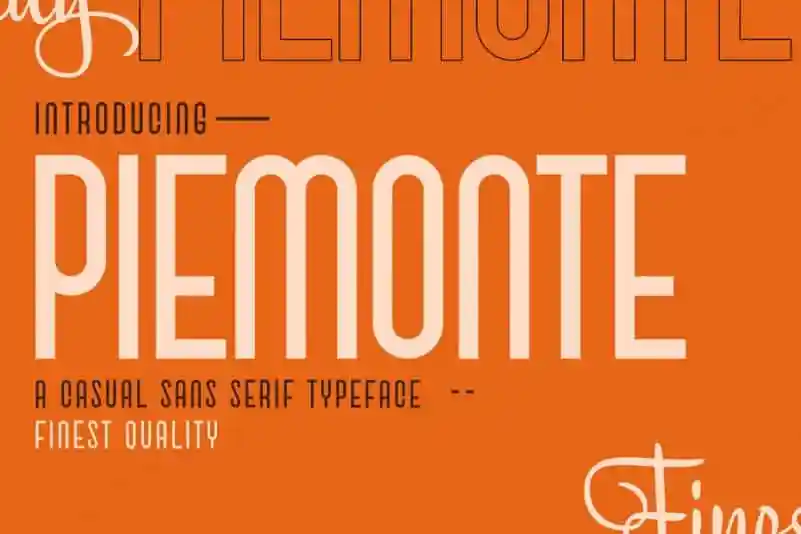
Piemonte Sans Serif Font – Download Grátis
A Pieto Sans Serif Font é uma tipografia séria moderna criada para introduzir um toque leve e alegre nos ambientes minimalistas. Esta bonita e profissional fonte se destaca como uma excelente opção para design gráfico, ideal para aplicar em campanhas de filme, headlines, letras geométricas, subtítulos, logomarcas, entre outros formatos. Com sua simplicidade agradável e seu toque cálido, a Pieto Sans Serif é perfeita para quem busca uma fonte moderna que se destaca de forma elegante em designs minimalistas. Ideal tanto para designers profissionais quanto para iniciantes no campo da design gráfico, esta fonte traz vida à sua próxima criação visual.